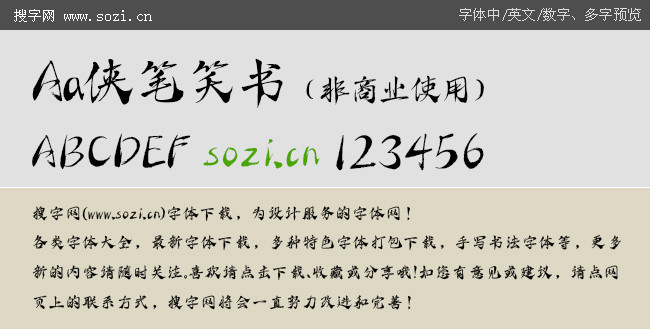
Aa俠筆笑書
搜字網(wǎng)給大家提供一款A(yù)a俠筆笑書(非商業(yè)使用)中文字體下載,該字體是一款手寫字體,字體書寫流暢,字形隨性灑脫,具有很好的視覺感,適用于平面宣傳設(shè)計(jì)、網(wǎng)頁設(shè)計(jì)、海報(bào)設(shè)計(jì)等應(yīng)用(此字體為個(gè)人非商用版,商用可以聯(lián)系QQ:1006760504)。